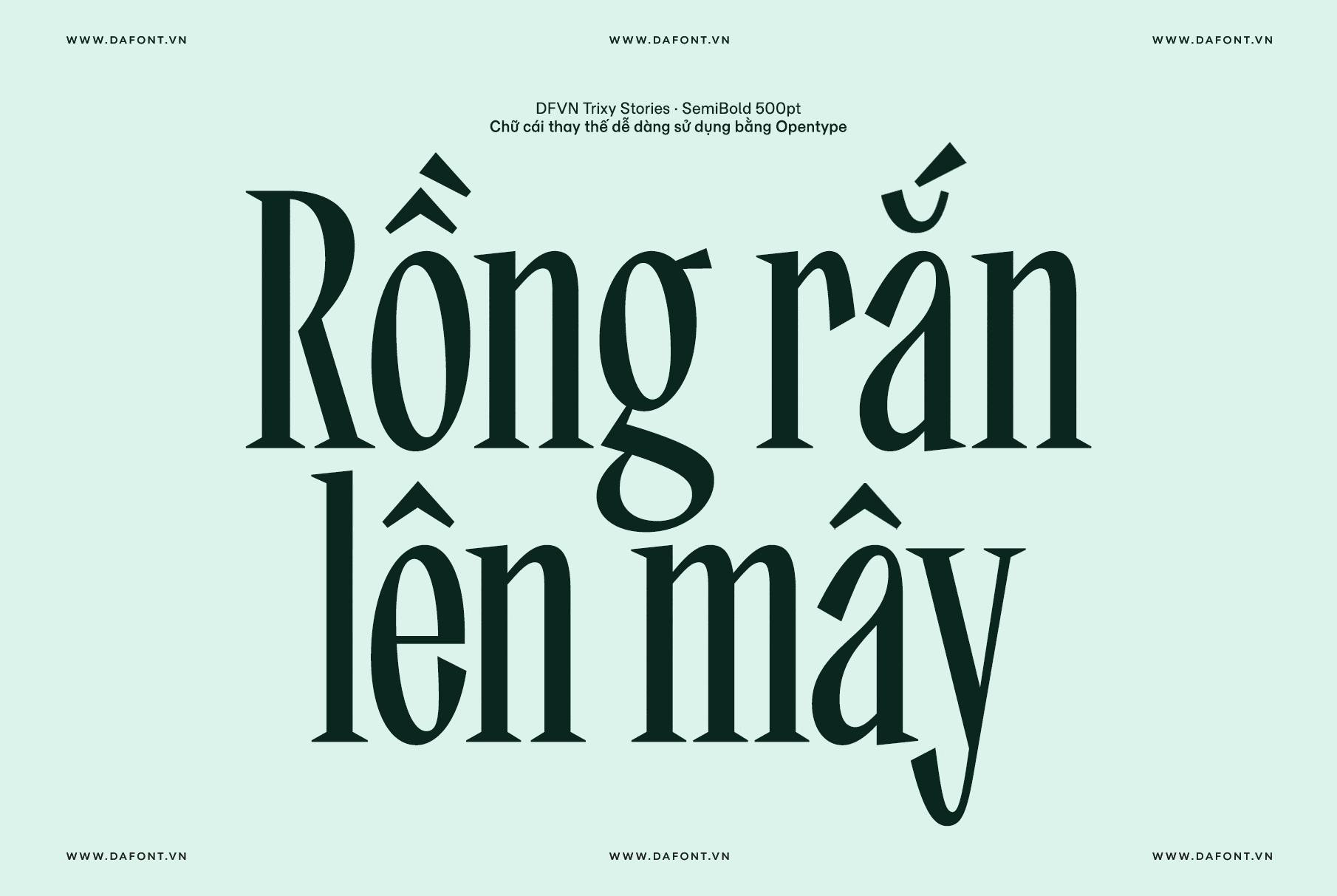
DFVN Trixy là bộ font serif condensed Việt hóa, được thiết kế cho typography display rất nổi bật với 10 style, phù hợp cho branding, editorial, packaging và poster hiện đại mang hơi hướng retro.
Trixy font – Cảm hứng từ ký ức Xô Viết
Trixy là typeface serif condensed (chữ có chân dạng hẹp) với độ tương phản nét mạnh, chân serif sắc và nhiều chi tiết “eccentric”, tạo cảm giác vừa retro vừa đương đại. Font được lấy cảm hứng từ lettering Cyrillic táo bạo trên bìa sách Xô Viết giữa thế kỷ 20, sau đó phát triển thêm Latin mở rộng. Trixy được định vị là font display chuyên dùng cho tiêu đề, logo, bìa sách, poster và các layout cần tạo ấn tượng thị giác mạnh.
Trixy là một family gồm 2 bộ font khác nhau với tổng cộng 10 style.
- Trixy Stories: 5 trọng lượng từ Light đến Bold, cảm giác tinh tế, biểu cảm, nhiều ligature và stylistic alternates để tạo chất editorial sang trọng.
- Trixy Tales: 5 trọng lượng từ Light đến Bold, chi tiết sắc hơn, phần chân ký tự kéo dài dạng swash giúp layout trở nên kịch tính và đậm tính “display”
Trixy Stories và Tales khác nhau gì?
Trixy Stories và Trixy Tales là hai “nhánh” trong cùng một bộ font, giống như hai giọng nói khác nhau của cùng một typeface, chủ yếu khác nhau ở sắc thái và mức độ “drama” trong hình dáng chữ.
Khác nhau về sắc thái tổng thể
- Trixy Stories: Mang phong cách tinh tế, biểu cảm, tone “refined” hơn, phù hợp khi bạn muốn cảm giác sang, editorial, giàu cảm xúc nhưng không quá gắt.
- Trixy Tales: Cá tính hơn, “bolder personality”, thiên về những layout cần impact mạnh, cảm giác nổi loạn, kịch tính và rất display.
Khác nhau về chi tiết hình dáng chữ
- Trixy Stories: Form chữ gọn, các chi tiết được tiết chế, hệ ligature và stylistic alternates phong phú giúp chữ mềm mại, mượt mà hơn.
- Trixy Tales: Đẩy độ biểu cảm lên cao hơn với chi tiết sắc hơn, chân chữ kéo dài kiểu swash‑like legs tạo đường kéo mắt rất mạnh trong tiêu đề.
Giống nhau (nhưng dùng khác ngữ cảnh)
- Cả Stories và Tales đều có 5 weight từ Light đến Bold, hỗ trợ Extended Latin + Cyrillic và đầy đủ OpenType features (ligatures, alternates, stylistic sets…).
- Stories hợp branding sang, editorial, bìa sách tinh tế; Tales hợp poster, packaging, key visual, tiêu đề cần gây ấn tượng mạnh hoặc vibe retro/experimental rõ hơn.
Gợi ý sử dụng nhanh- Dùng Stories khi: logo cao cấp, tạp chí, book cover giàu cảm xúc nhưng vẫn thanh lịch.
- Dùng Tales khi: poster sự kiện, bìa album, packaging muốn “đập vào mắt”, cần các chân chữ kéo dài tạo hiệu ứng đồ họa.
Đặc điểm thiết kế và tính năng
Về mặt hình thái, Trixy sở hữu thân chữ hẹp (condensed), độ tương phản dày – mỏng cao, chân serif dựng thẳng và nhiều chi tiết lạ như những đường cong phá cách hoặc chân kéo dài. Điều này giúp font giữ được tính đọc được ở kích thước lớn, đồng thời tạo hiệu ứng “impact” mạnh mẽ trên tiêu đề. Cảm hứng vintage nhưng cách xử lý form hiện đại khiến Trixy hợp với các thương hiệu muốn nhìn vừa cổ điển vừa tươi mới.
Trixy được phát triển từ bộ ký tự Cyrillic gốc và mở rộng sang Latin mở rộng, vì vậy nó phù hợp với nhiều ngôn ngữ châu Âu và các thị trường sử dụng Cyrillic. Bộ font tích hợp full OpenType features: ligatures, alternates, stylistic sets, localized forms, case sensitive forms… giúp bạn tùy biến chữ theo nhiều phong cách khác nhau trong một family.
Ứng dụng thực tế của Trixy
Với tỷ lệ hẹp (Condensed) giúp tiết kiệm không gian ngang nhưng vẫn giữ được độ cao ấn tượng, DFVN Trixy là “vũ khí” hoàn hảo cho:
- Branding & Packaging: logo, nhãn chai, hộp sản phẩm, bao bì mang tính hoài cổ, nghệ thuật.
- Editorial & Publishing: tiêu đề tạp chí, bìa sách, trang mở đầu chapter, pull quote.
- Advertising & Posters: key visual cho chiến dịch quảng cáo, poster sự kiện, concert, triển lãm.
- Digital & Web Design: hero heading trên website, cover social media, visual cho campaign online.
Ví dụ, bạn có thể dùng Trixy Stories Light/Bold cho tựa bài editorial sang trọng, và Trixy Tales Bold cho poster âm nhạc hoặc bìa sách mang vibe retro mạnh.
DFVN Trixy Việt hóa Preview
Bộ font DFVN Trixy được Việt hóa cẩn thận, tất cả các ký tự và dấu được tối ưu hóa lại cho phép hiển thị tốt hơn, kerning toàn bộ ký tự. Không chỉ Việt hóa bộ ký tự cơ bản, toàn bộ ký tự thay thế (alternates/stylistic sets), chữ ghép (ligatures)… cũng được Việt hóa đầy đủ. Bạn chỉ cần bật OpenType trong các phần mềm hỗ trợ là dùng ngay